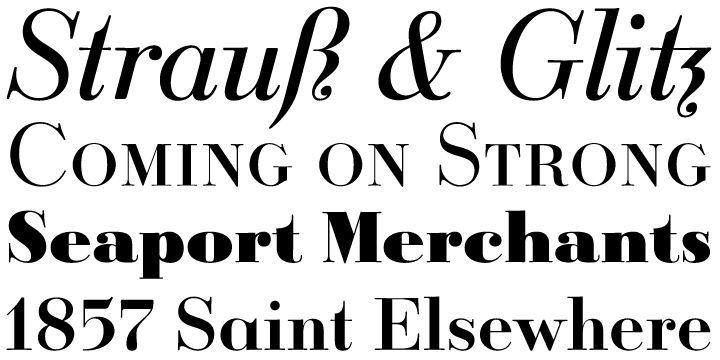
Ratio-Latein digital
Nach der Orpheus haben die Leute von Canda Type nun auch die Ratio-Latein digitalisiert. Macht auf den ersten Blick einen ganz guten Eindruck; ich habe sie mir aber noch nicht näher angesehen. Genauso wie die Digitalisierung der Orpheus ist auch diese Schrift wieder für Textgrößen völlig ungeeignet.
Genauso wie die Digitalisierung der Orpheus ist auch diese Schrift wieder für Textgrößen völlig ungeeignet.
wobei ich sagen würde das war bei den alten bleisschriften auch nicht anders.
beide zeigen ihre stärken ja eher in headlinegrößen.